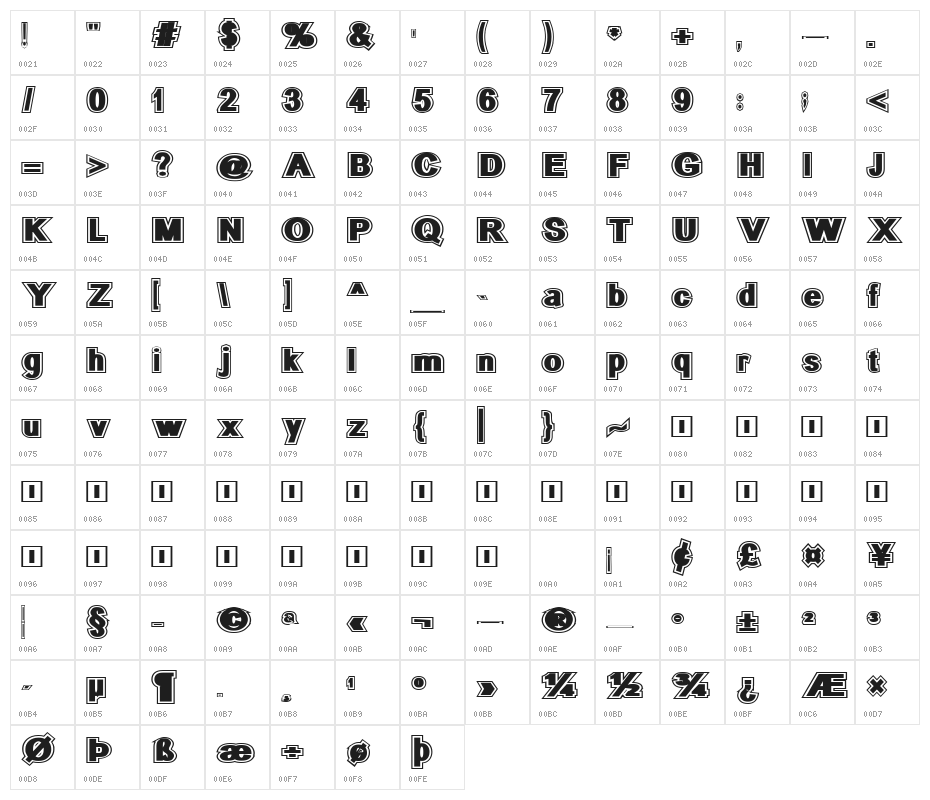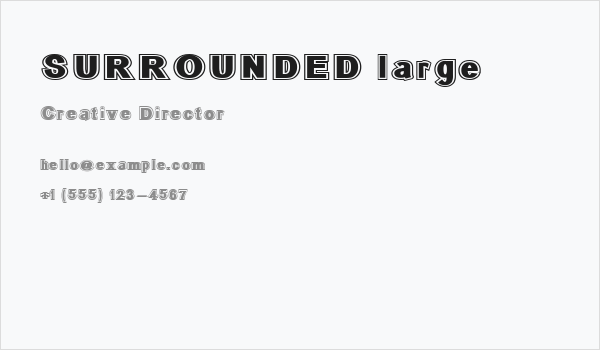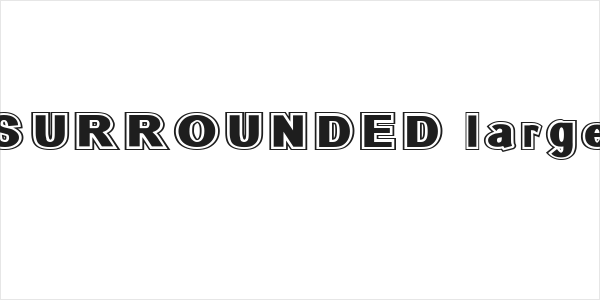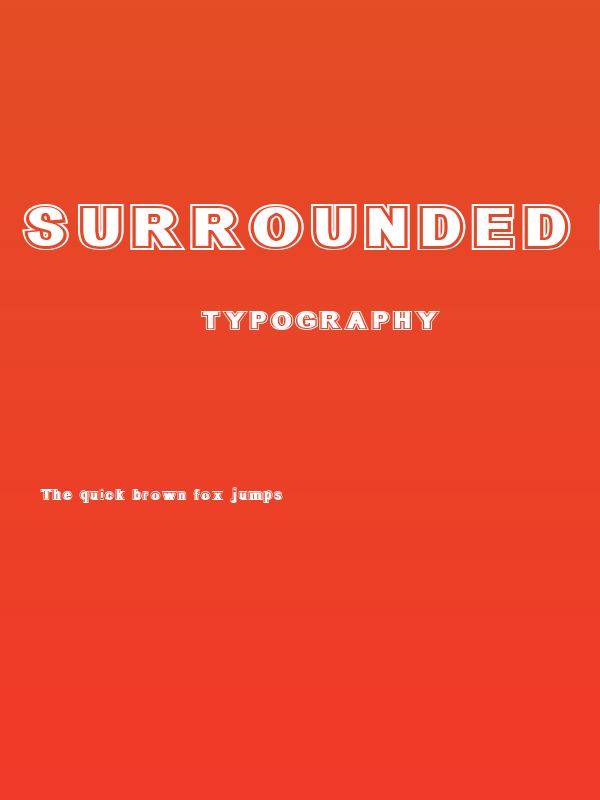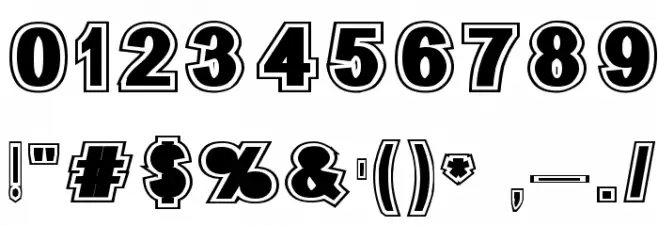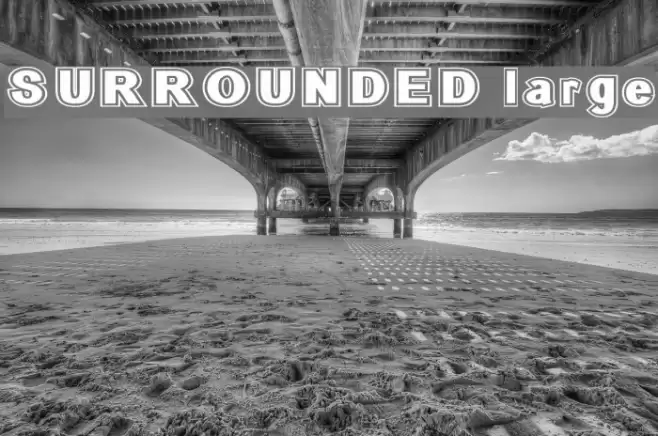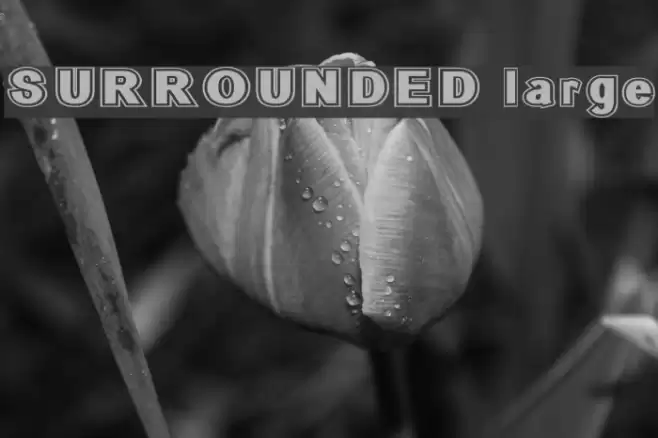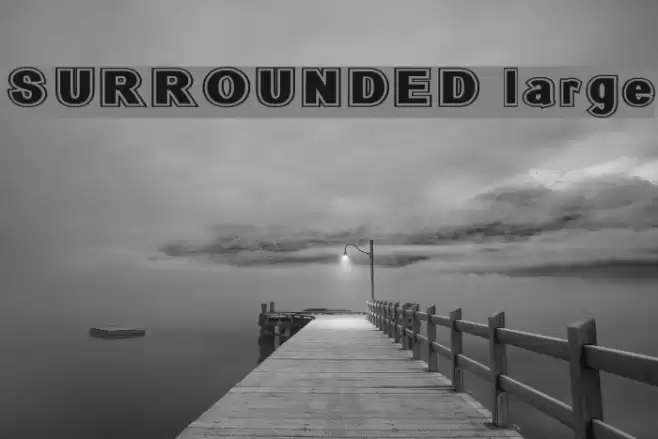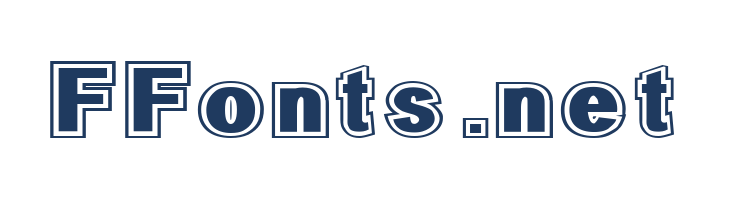
SURROUNDED large Font
✎ Outline
| Vorgeschlagene Projekte | Ideal for posters, headlines, logos, and branding materials that require a bold and attention-grabbing typeface. |